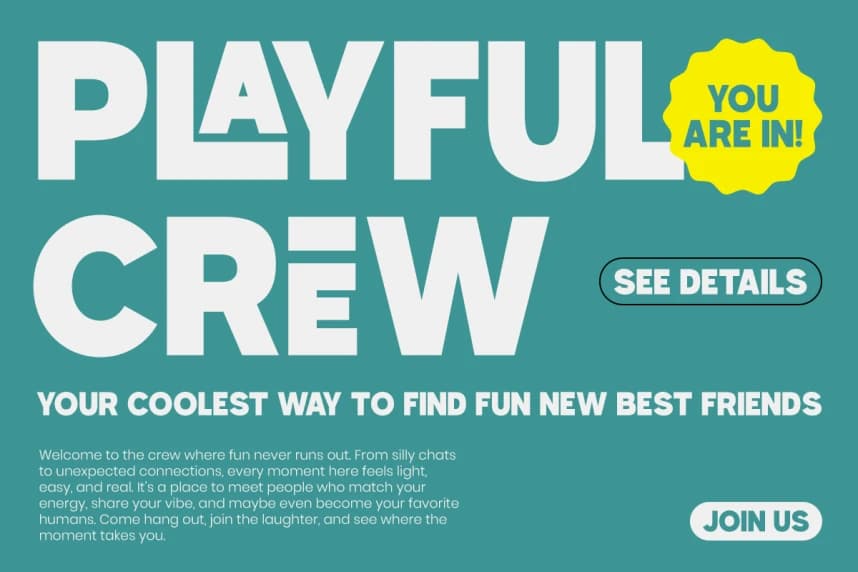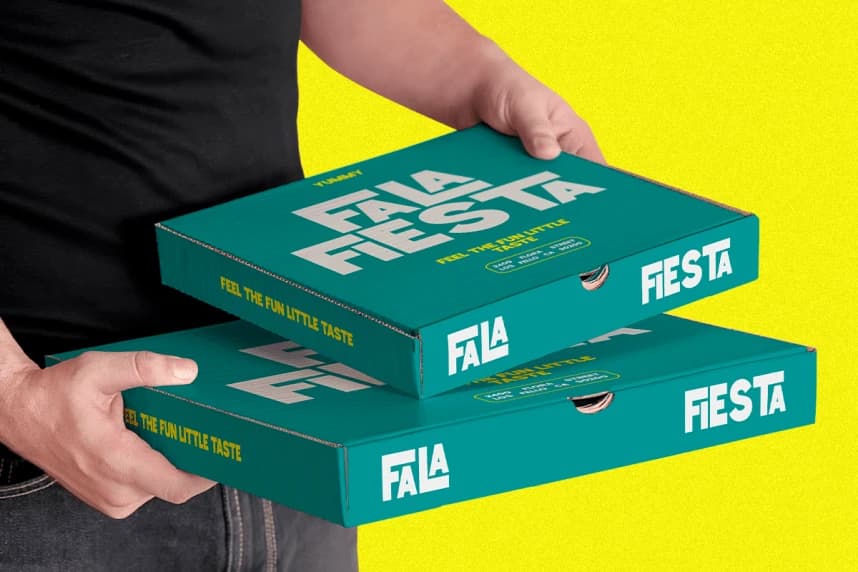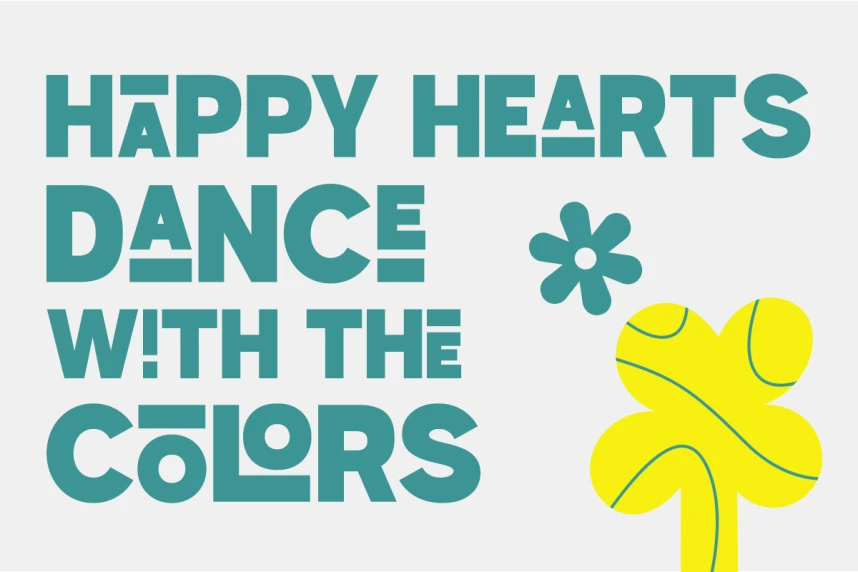
Yağmur Ormanı Yazı Tipi
Rain Jungle Font, anında görsel etki yaratmak için tasarlanmış kalın bir gösterim sans-serif yazı tipidir. Kalın geometrik biçimleriyle, eğlenceli modern yapısı ve güçlü başlık etkisiyle bu yazı tipi, cesur marka enerjisi ile mükemmel bir denge sunar.
Rain Jungle Font, anında görsel etki yaratmak için tasarlanmış cesur bir gösterim sans-serif yazı tipidir. Kalın geometrik şekillerine, eğlenceli modern yapısına ve güçlü başlık görünümüne sahip olan bu yazı tipi, cesur marka enerjisi ile mükemmel bir denge sunar.